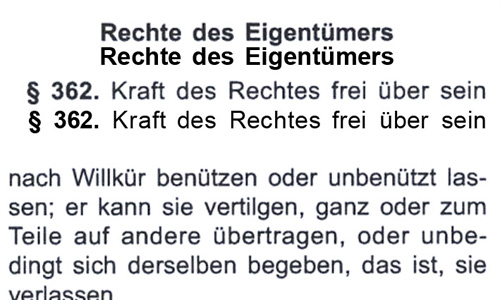
Schrift aus Gesetzestexten
Hier also der Ausschnitt:
also arial hätte ich schon versucht (ausgedruckt und daneben gehalten), auch in verschiedenen schriftgrößen (7.5, 8, ..) aber leider schauts trotzdem nicht gleich aus.
kennt jemand vielleicht noch eine schriftart, die ARIAL sehr ähnlich ist, und die es sein könnte?
(ausgedruckt und daneben gehalten), auch in verschiedenen schriftgrößen (7.5, 8, ..) aber leider schauts trotzdem nicht gleich aus.
naja dein ausdruck kannnst du nicht mit einem ooffset druck vergleichen, wenn es der fall sein sollte.
mach do mal ein scann von einem oder zwei wörtern und das ganze gröesser,
dann kann man es genauer sagen.
für mich ist das die ARIAL
Joh, ich hatte das posting gelöscht ...
Ich hatte auch zuerst auf Arial getippt, dann wurde ich unsicher.
Dann die Akzidenz Grotesk* ins Spiel gebracht. Dann wurde ich wieder unsicher, hehe. :D
Also irgendetwas zwischen Arial und AG.
*es gibt ja auch die verwandte Basic Commercial von Linotype
okay, dann finde ich mich damit ab, dass es am druck liegen muss.
Könnte auch die Helvetica sein *duck und weg* :lol:
nicht im geringsten, zu sehen am rundlichen fuss des R, den leicht angeschnittenen strichenden in c und e sowie dem schrägen dach des t.
aber du hast ja ein :lol:-smilie hinter deinen satz gesetzt.. also wars wohl doch nur ein witz.
ja, aber ich kann texte mittlerweile anhand ihres grauwerts zwischen arial, akzidenz grotesk und helvetica unterscheiden.. die sind nämlich definitiv sehr unterschiedlich.